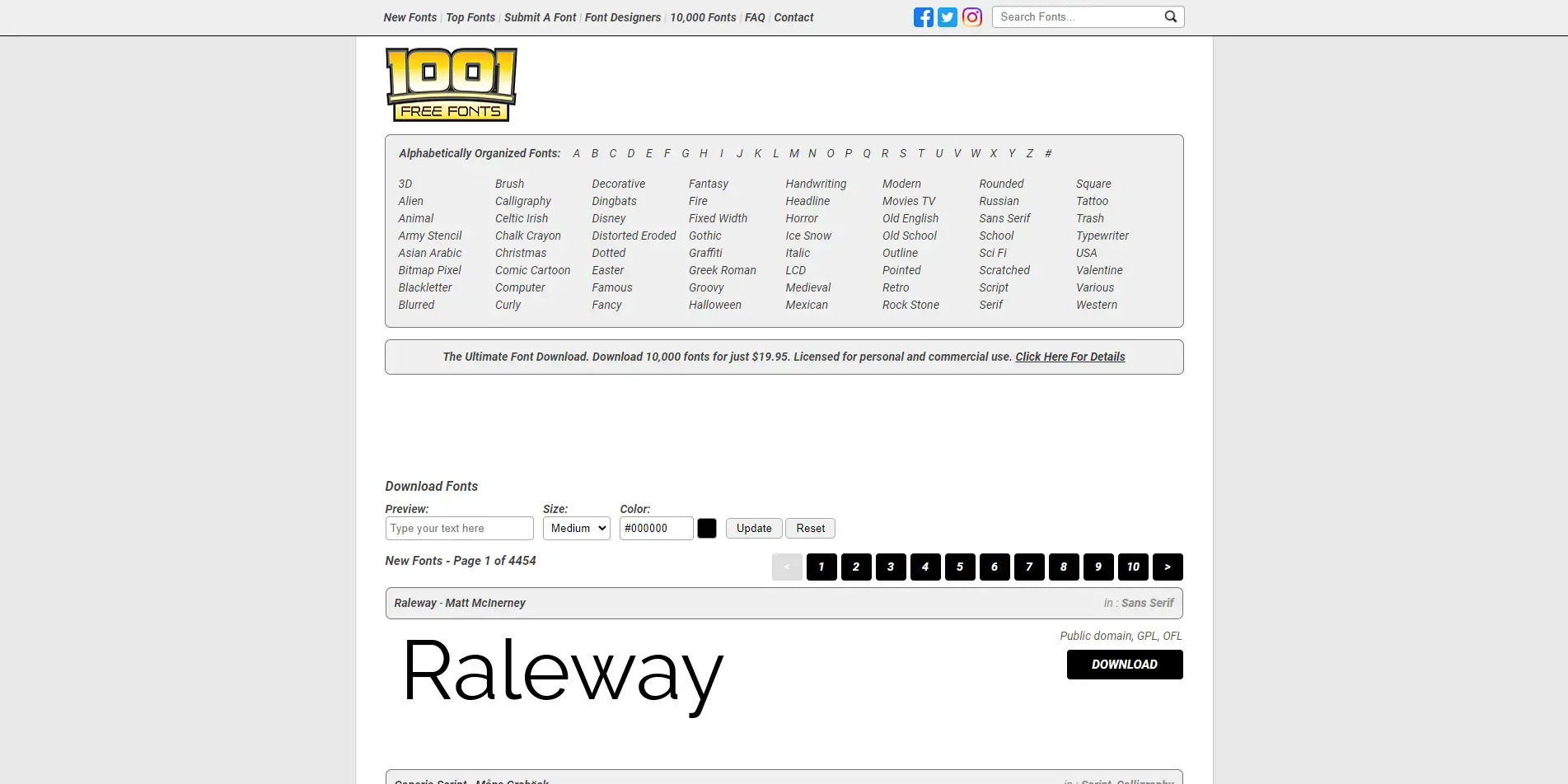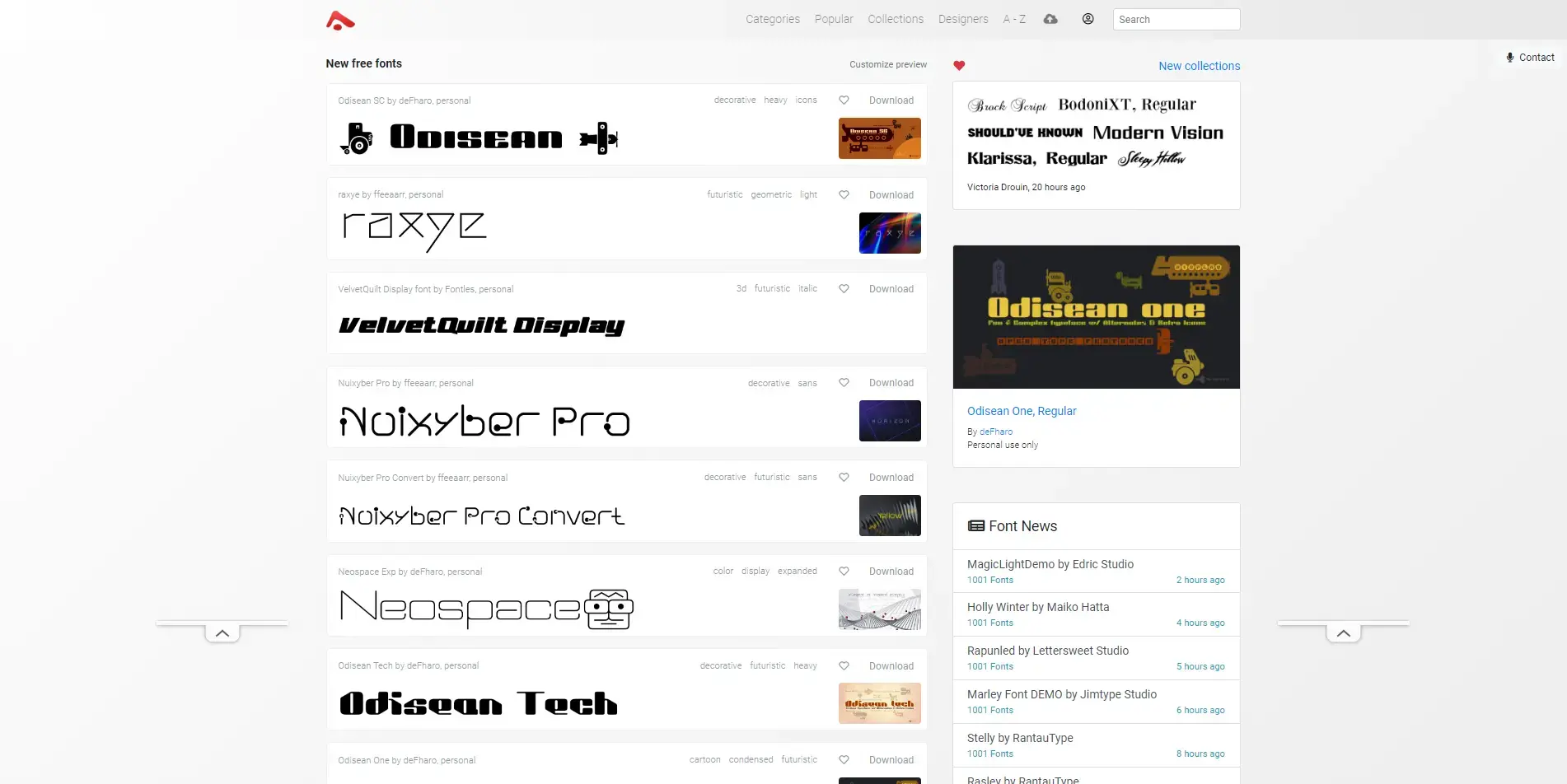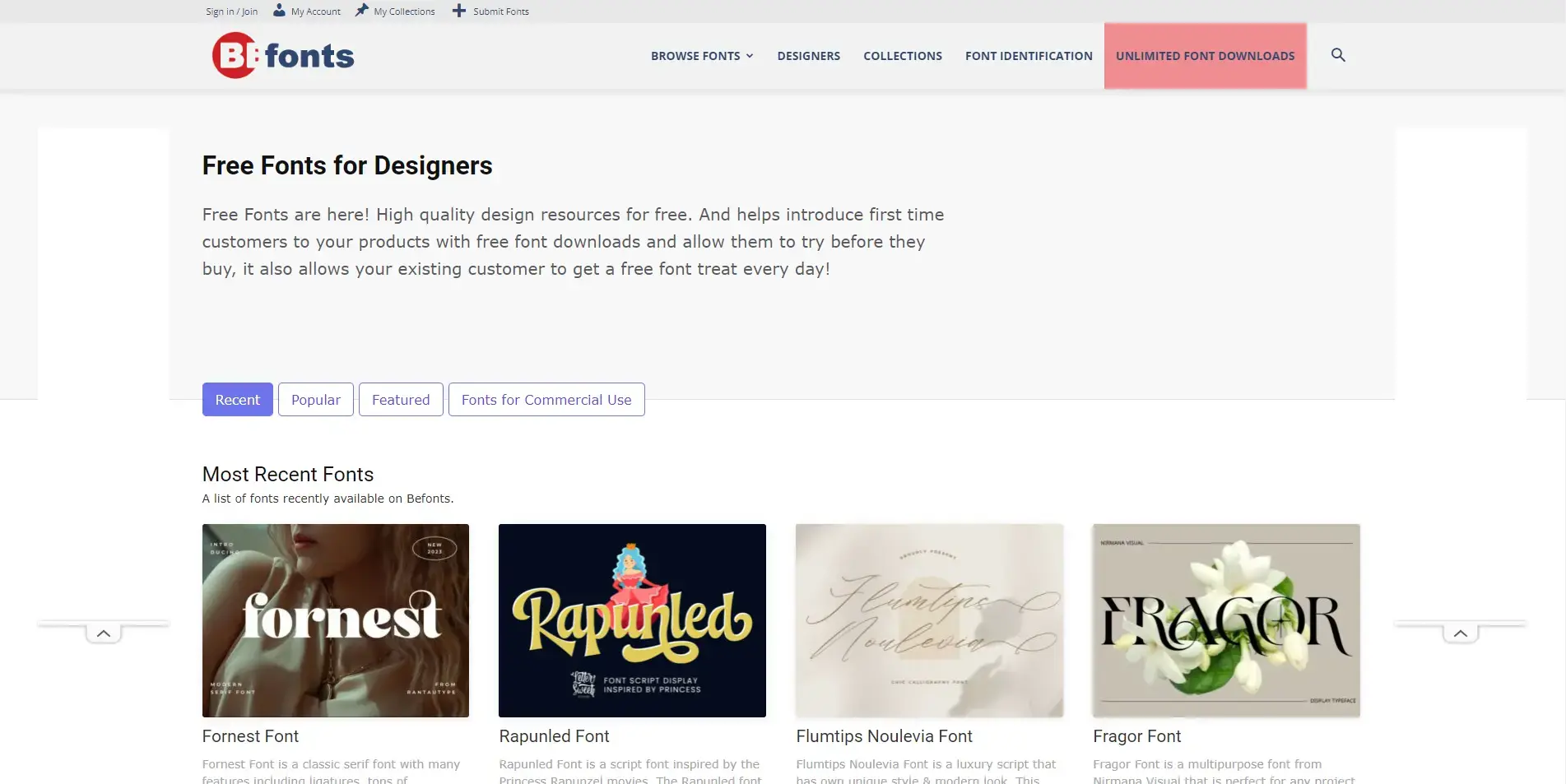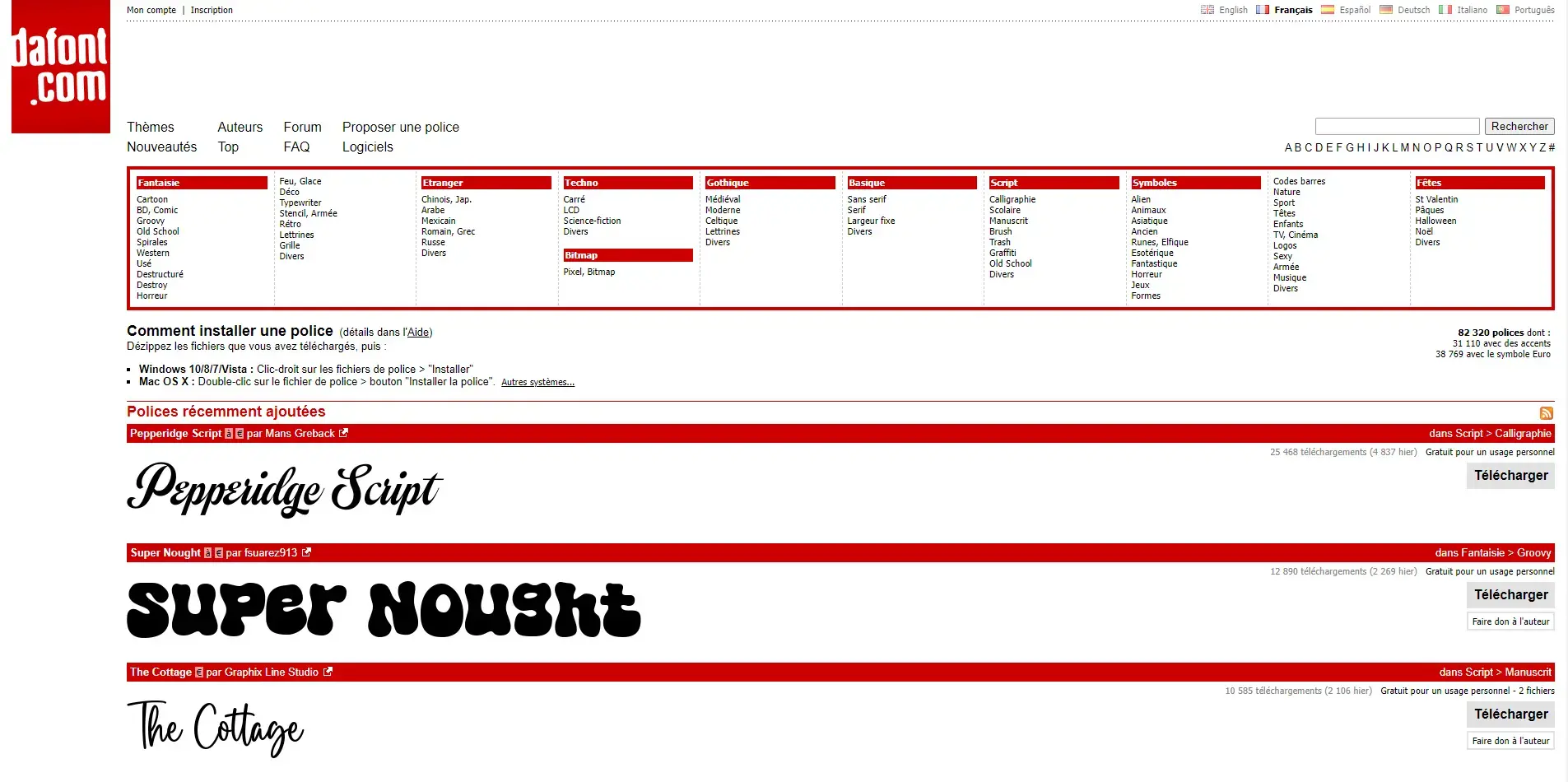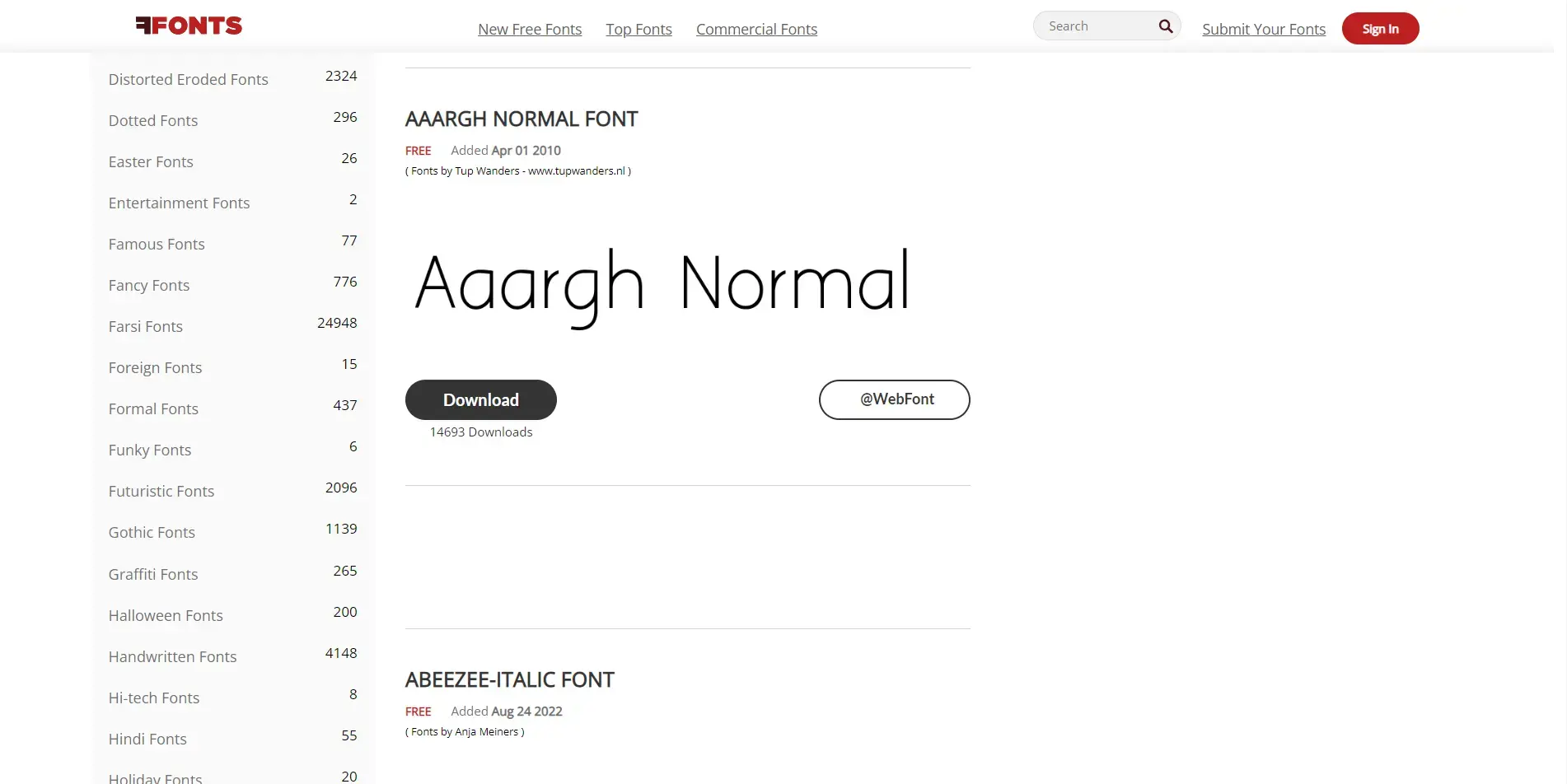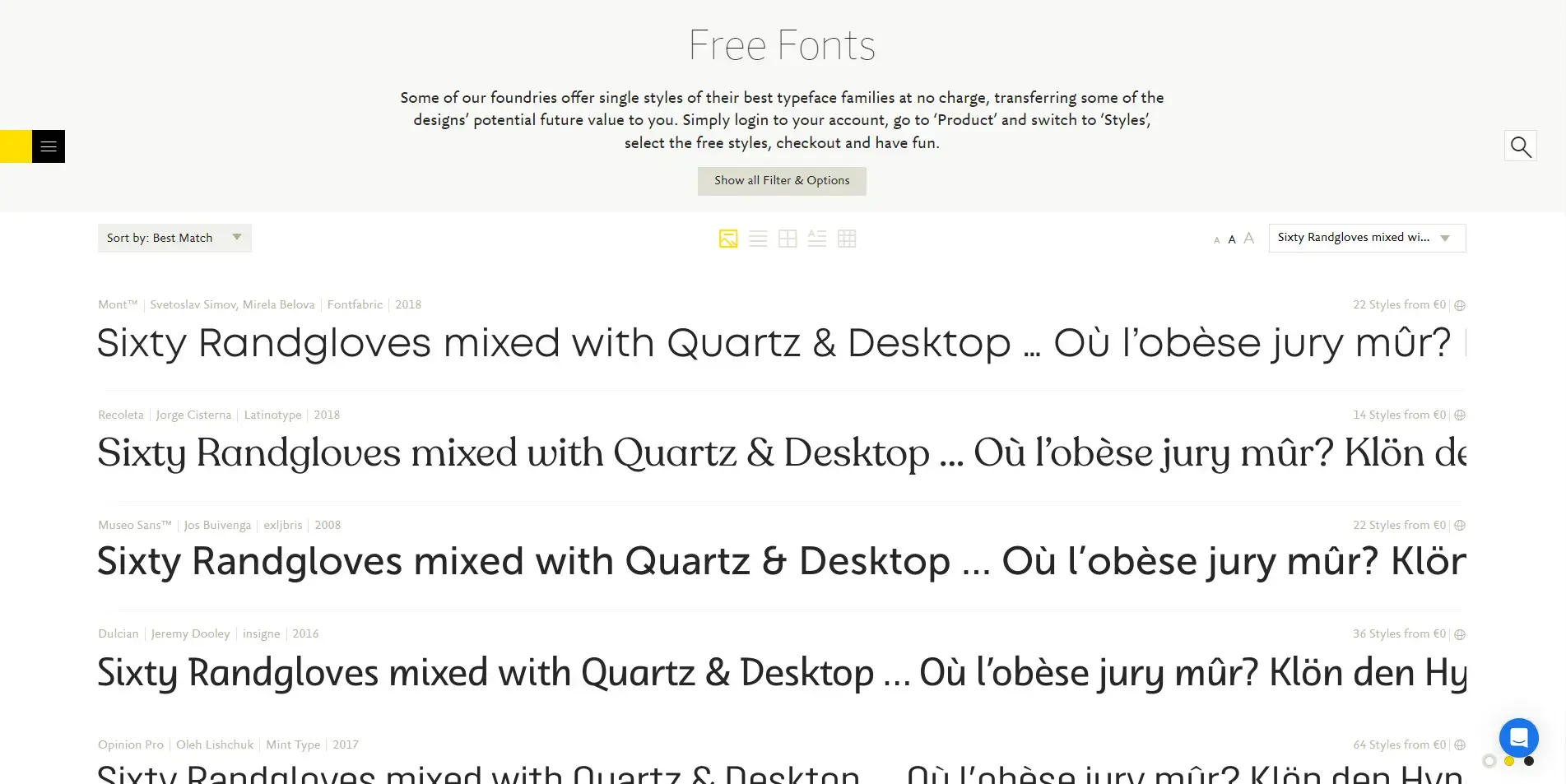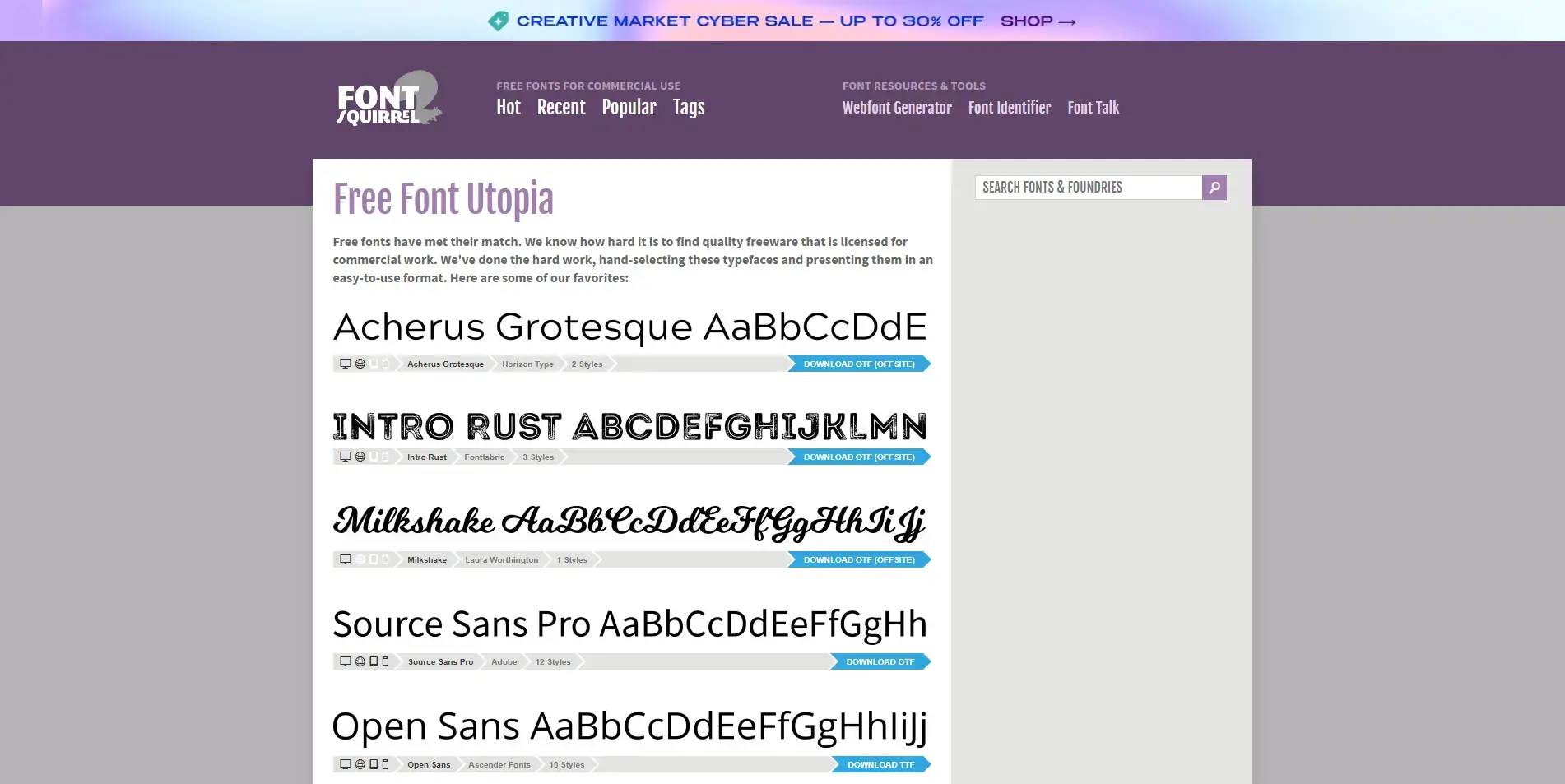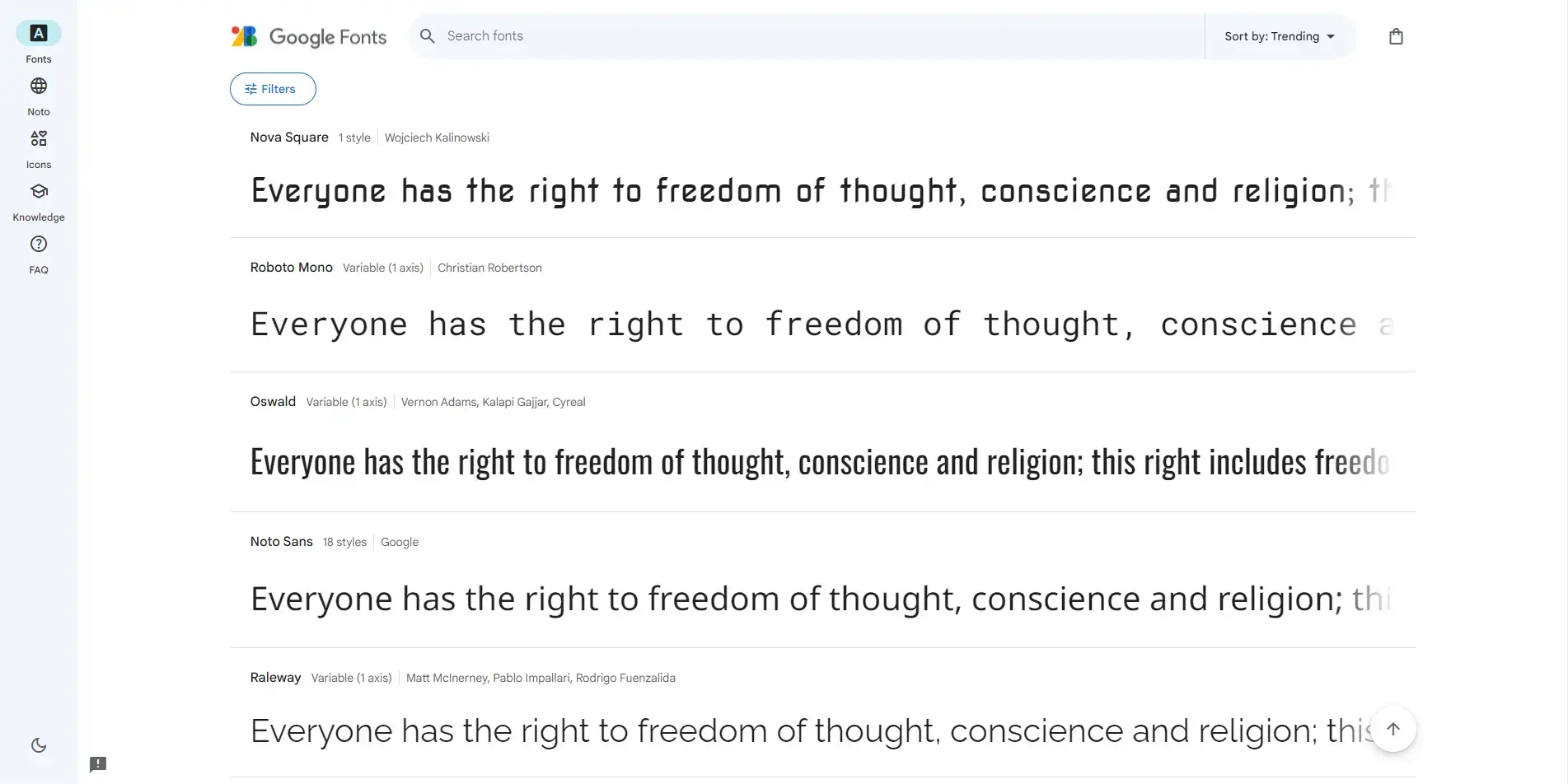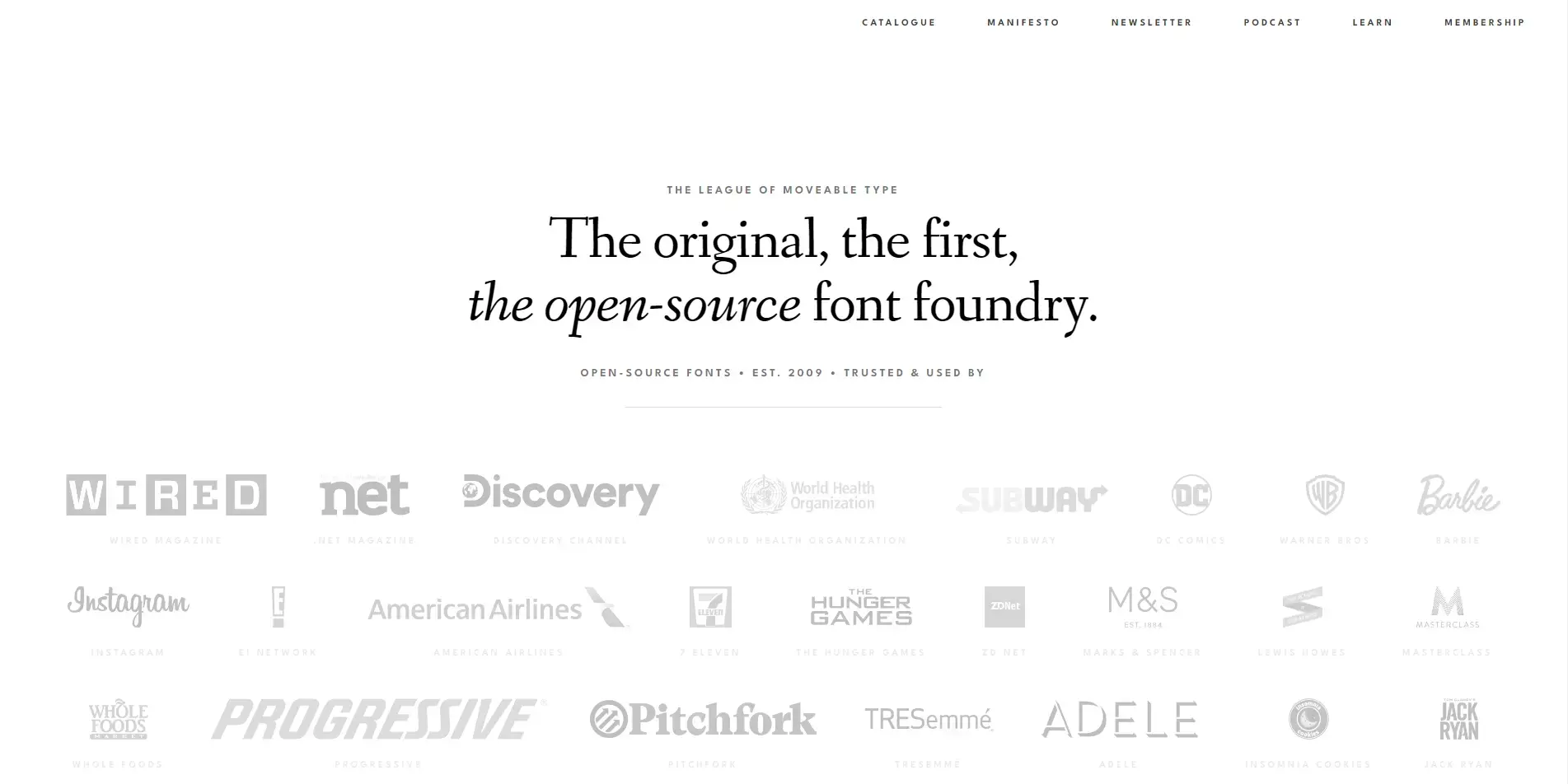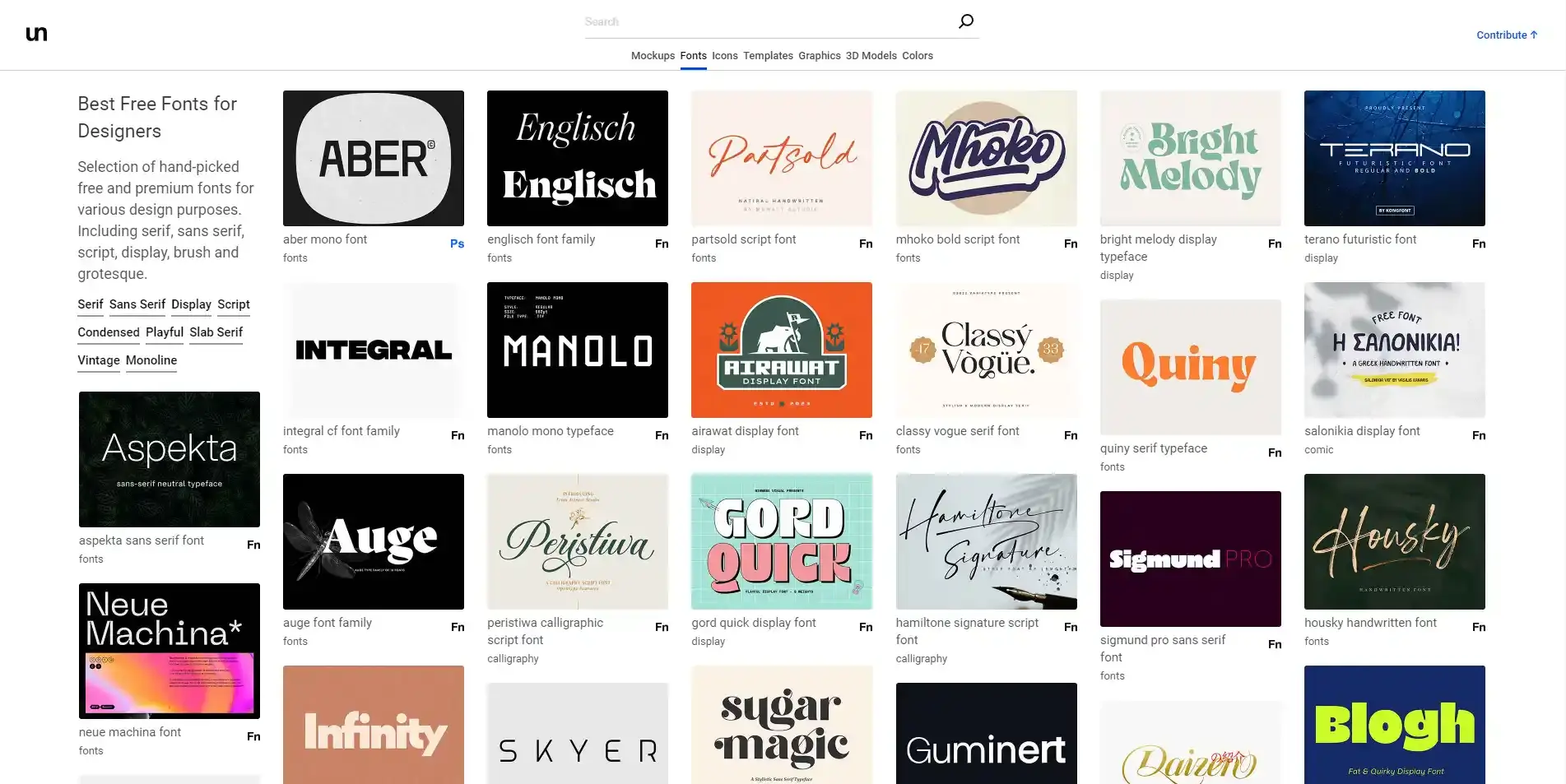
Les sites de police d’écriture en ligne gratuite
Il est parfois difficile de trouver une police d’écriture reflétant l’esprit de votre marque tout en se démarquant des autres. Nous avons sélectionné pour vous plusieurs sites de police d’écriture en ligne gratuite qui vous aideront dans la recherche de vos fonts.
Ces moteurs de recherche de fonts gratuites sont très utiles pour trouver la police d’écriture qui correspond à vos besoins. En effet, ces sites proposent une large gamme et vous pouvez facilement trouver votre bonheur. Vous pourrez ainsi choisir une police pour le logo de votre entreprise, pour votre marque ou encore des caractères spécifiques pour vos textes.
Dafont
Dafont est un excellent site de police d'écriture en ligne gratuite. Il y a une très grande sélection de polices d'écriture disponibles, et vous pouvez facilement les télécharger et les utiliser sur votre ordinateur. Les polices d'écritures de Dafont.com sont faciles à installer et à utiliser, et elles offrent une bonne qualité d’impression.
FontSquirrel
Fontsquirrel est un excellent site de police d'écriture en ligne avec beaucoup de styles différents et disponibles pour un usage pro ou perso. Les polices d'écritures gratuites sont triées par thèmes et il y a une option de recherche avancée disponible si vous avez des exigences spécifiques. Le site web est extrêmement facile à naviguer et les polices d'écritures sont téléchargeables au format ZIP, ce qui est pratique.
• Consultez des bases de données de polices : explorez des bases de données en ligne comme Identifont qui vous posent une série de questions sur les caractéristiques de la police pour vous aider à l'identifier.
Lors de l'utilisation de ces méthodes, soyez attentif aux résultats, car la reconnaissance peut varier en fonction de la qualité de l'image ou des caractéristiques spécifiques de la police. En combinant plusieurs approches, vous augmentez vos chances de retrouver la police d'écriture que vous cherchez.